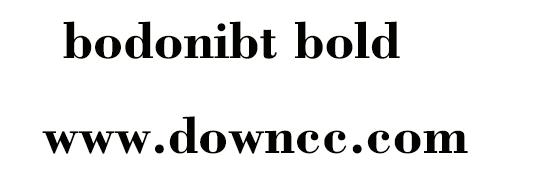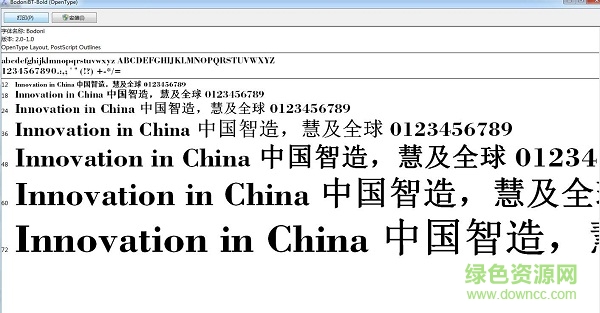
軟件介紹 軟件標簽: bodoni 英文字體 bodonibt bold字體是一款較粗的襯線字體,外形靈巧精致,十分美觀,字面簡潔清晰,適合長時間閱讀,用在電子手冊、ppt、期刊、廣告等方面都可以,喜歡的朋友趕緊來本站下載收藏吧!字體設計術語介紹Arm:字臂 Shoulder:字肩 Stem:主干 Serif:襯線 Ascender:上伸部 descender:下伸部 Baseline:基準線 相關字體推薦bodoni 72 oldstyle 授權:免費軟件 WinAll, WinXP, Win7大小:2.4M語言:中文bodoni72字體包收錄了bodoni72smallcaps、bodoni72oldstyle以及bodoni72bold等字體,氣質優(yōu)雅,線條清晰,具有出色的辨識度,需要的朋友快來下載吧!優(yōu)秀西文字體推薦【Avenir】字形簡潔,現(xiàn)代,雖然也有幾何特征下載地址bodoni mt condensed 普通 授權:免費軟件 WinAll, WinXP, Win7大小:45KB語言:中文bodonimtcondensed字體是一款普通襯線字體,字體結構設計新穎而不失規(guī)矩,字形優(yōu)美,表現(xiàn)力強,用在廣告、雜志、宣傳畫報等方面非常合適,歡迎需要的小伙伴們前來下載!bodoni字體推薦襯線字體介紹【didot】現(xiàn)代襯線下載地址bodonibt bold字體安裝方法方法一:控制面板/字體/文件/安裝新字體;方法二:直接將字體復制到C:\WINDOWS\Fonts。方法三:針對win7系統(tǒng),用戶只需選中字體右鍵安裝即可。 軟件截圖 上一張下一張(1 / 1) 安裝詳細截圖 其他版本下載 標題 大小 更新日期 下載 下載地址 電腦版 bodonibt bold 點擊報錯 軟件無法下載或下載后無法使用,請點擊報錯,謝謝! 關閉報錯反饋 請描述您所遇到的錯誤,我們將盡快予以修正,謝謝! *必填項,請輸入內容 本類最新 sounso beauty字體 spyced哥特英文字體 ttf版 zerodegrees字體 the next font ttf版 coolvetica font keep calm ttf 免費版 相關文章 俠客風云傳攻略 我叫mt4哪個職業(yè)輸出最高 我叫mt4輸出最高的職業(yè)排行 在Windows 2003中配置ASP.Net環(huán)境 ACCESS數據庫中Field對象的caption屬性讀寫 Linux/UNIX命令dd簡介 應用:基于Unix的Web服務器安全指南 用戶評論 熱門評論 最新評論 發(fā)表評論 查看所有評論(0) 昵稱: 請不要評論無意義或臟話,我們所有評論會有人工審核. 字數: 0/500 (您的評論需要經過審核才能顯示)